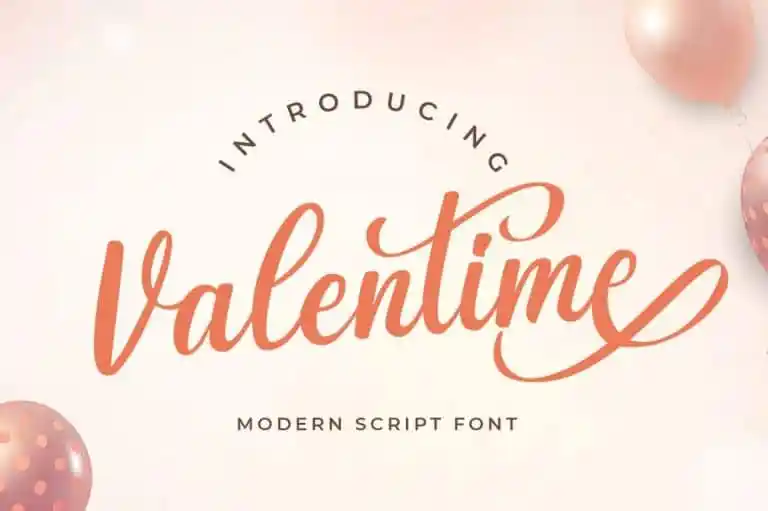
Valentime Script Font – Download Grátis
Avalon Script Font é uma elegante fonte de script criada pela Hugefonts com curvas leves e amoras enlaçadas que adicionam um toque único aos seus projetos. Esta fonte foi especialmente concebida para representar a beleza e a personalidade descontraída, tornando-a perfeita para qualquer projeto em que você esteja trabalhando. Seu formato delicado e sua disposição cuidadosamente planejada permitem um contraste suave entre a seriedade e o humor, permitindo uma variedade de usos criativos e impactantes. A Avalon Script Font é mais do que simplesmente um recurso para textos digitais – ela se transforma em um elemento visual poderoso capaz de destacar seu trabalho em qualquer plataforma digital ou impressão.